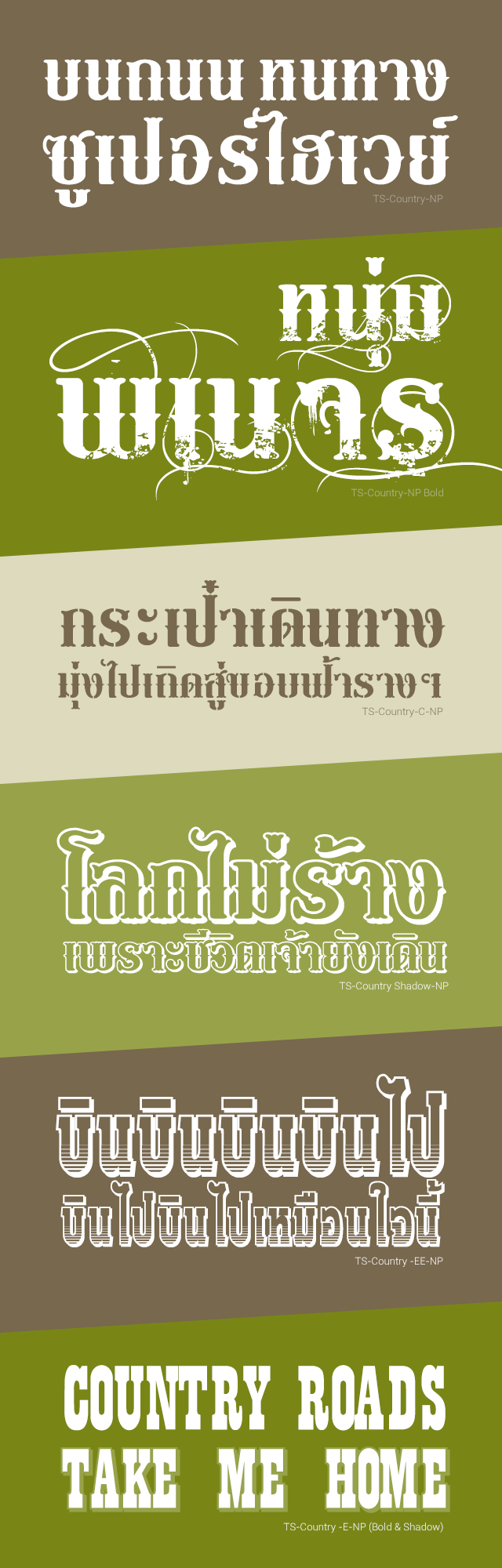
TS-Country-NP
มาอีกแล้วครับ ฟอนต์ใหม่จากอาจารย์ธง TS Font ที่คราวนี้มาในแนวลูกทุ่งฝรั่ง คันทรีๆ เหมือนหนังคาวบอย มีมาทีนึงน้ำหนักเดียวคงไม่พอ พี่แกเลยจัดมาซะเต็มครับ นับสไตล์กันไม่ถูกเลยทีเดียว ดูภาพกันเลยดีกว่า
จะเห็นได้ว่าถึงฟอนต์ชุดนี้จะเป็นเซ็ตที่ชื่อเดียวกันว่า TS-Country แต่เอาเข้าจริงก็มีหลากหลายสไตล์ ทั้ง TS-Country-NP (สไตล์หลัก), TS-Country-NP Bold (แบบย้วยๆ), TS-Country-C-NP (แบบเอาไว้ตัดพ่นลงบนป้าย), TS-Country Shadow-NP (เป็นเงาโปร่ง เอาไว้ประกอบกับสไตล์หลักแบบฟอนต์ส้มตำก็ได้นะครับ), หรือแม้แต่ TS-Country-E-NP (ไม่มีภาษาไทยนะ) และ TS-Country-EE-NP ที่เป็นอีกสไตล์ แต่ขอรวมอยู่ในตระกูลคันทรีเหมือนๆ กัน เชิญโหลดและเลือกใช้ได้ตามสะดวกเลยจ้ะ ชอบไม่ชอบ มีข้อผิดพลาดพรือแนะนำประการใดก็เชิญคอมเมนต์ได้นะ